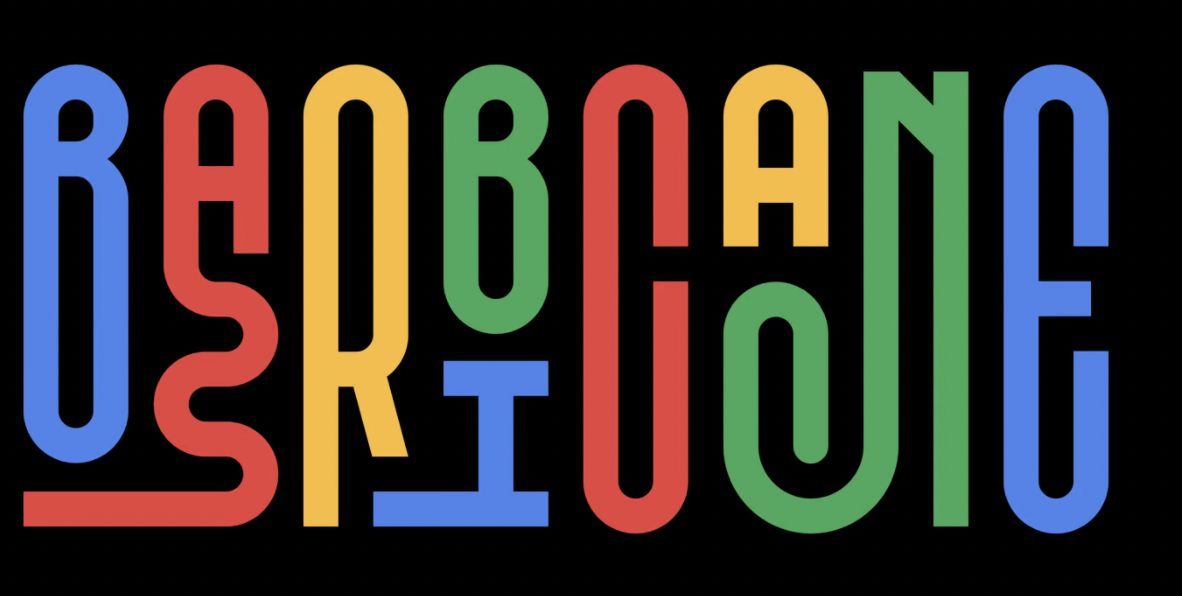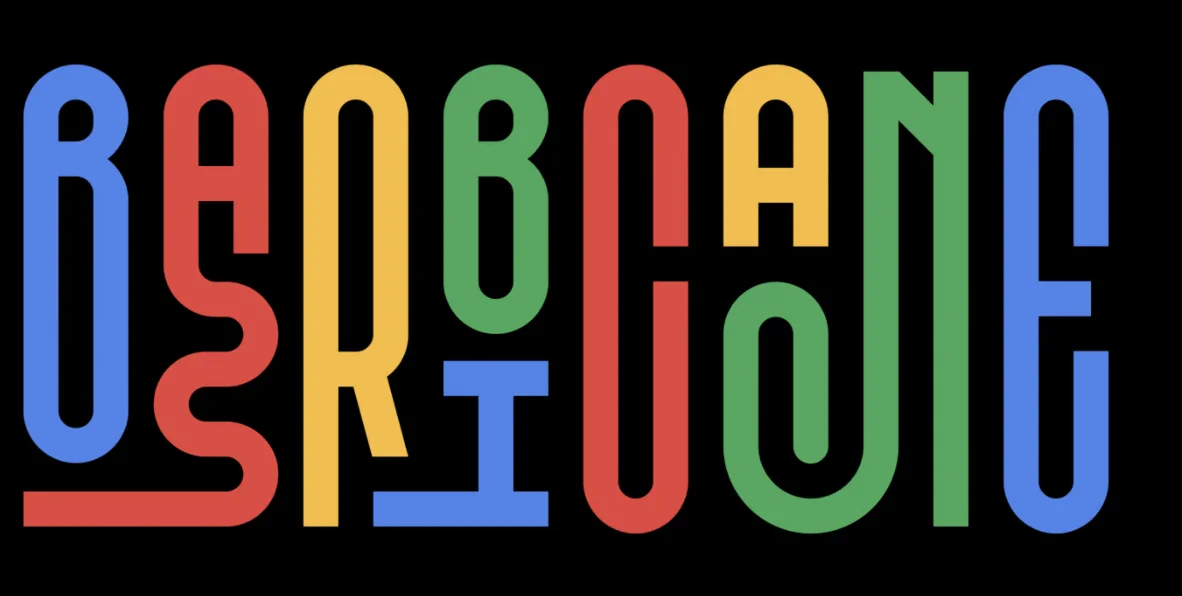
Название: SK Barbicane Font (2021)
SK Barbicane - это семейство шрифтов, названное в честь знаменитой книги Жюля Верна "С Земли на Луну". Вдохновленный предвидением Жюля Верна, он был разработан с синтезом будущего и прошлого. Несмотря на более четкие и футуристические линии, чем в будущем, он также включает в себя органическую структуру прошлого.
В этом шрифте все символы имеют равные размеры, моновес и монопробел. Таким образом, вы можете создавать регулярные типографские макеты в своих проектах. Состоящий из двух различных семейств, Normal и Unicase, этот шрифт имеет в общей сложности 12 различных шрифтов и 5088 глифов. Таким образом, он содержит множество типографских элементов, которые понадобятся вам в ваших проектах.